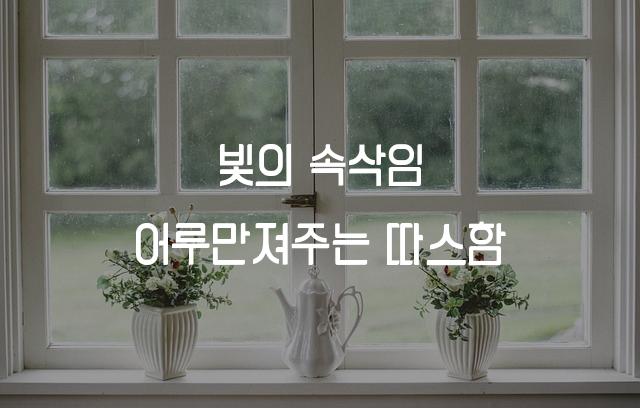
116수박화체는 WOO 제작사에서 만든 장식적인 고딕 폰트로, 독특한 각진 디자인과 기울어진 형태가 특징입니다. 이 폰트는 현대적 감성과 전통적 요소가 결합된 독창적인 스타일을 제공합니다.
116수박화체은(는)
기본 고딕, 장식 스타일, 기울임, 네모꼴, 단단함, 별모양/패턴 계열의 생김새를 가지고 있으며
어린이 책, 인사말 카드, 소셜 미디어 등에서 자주 활용되며, 효과적인 메시지 전달에 적합합니다.
이 폰트는 음식/식음료, 엔터테인먼트, 유아/가족 분야에 잘 어울리며,
친근한, 귀여운, 재미있는 느낌을 담고 있는 것이 특징입니다.
이 폰트와 유사한 폰트로는 고딕체, 나무체, 하늘체 등이 있어요. 함께 비교해 보시면 좋습니다!